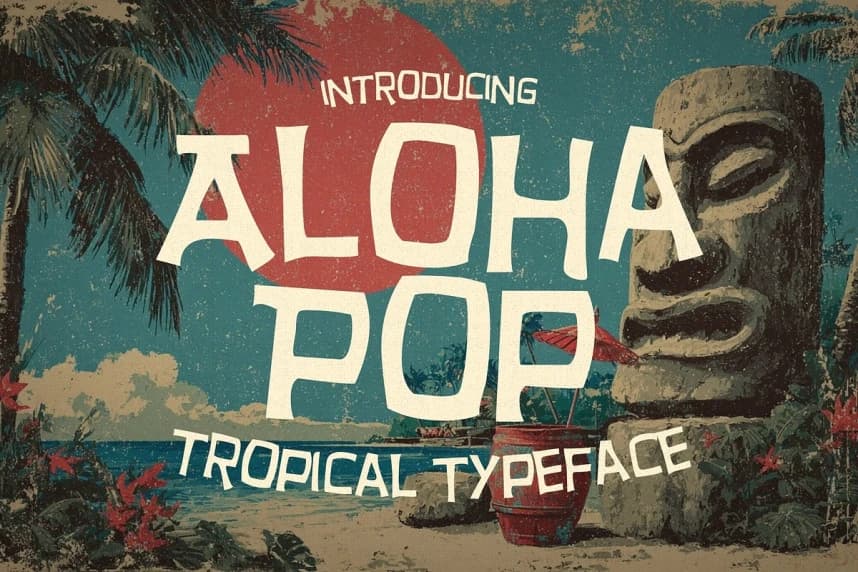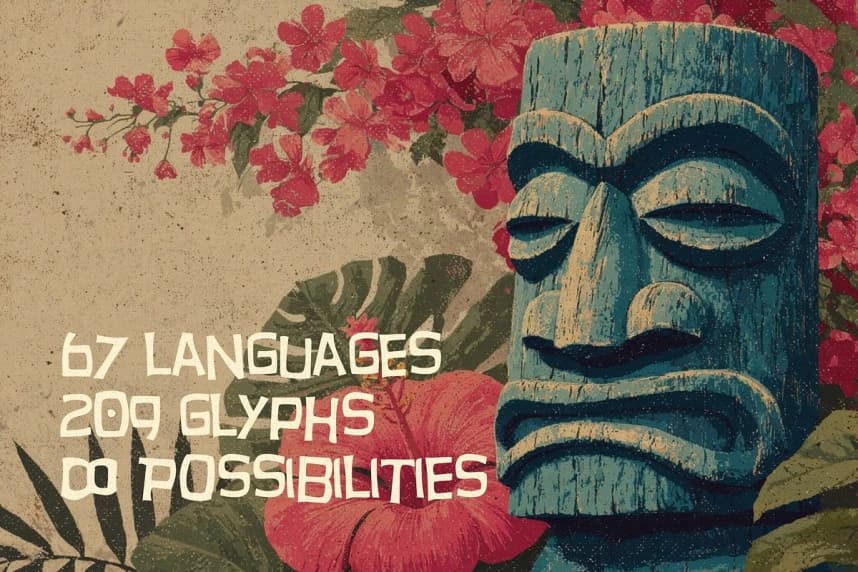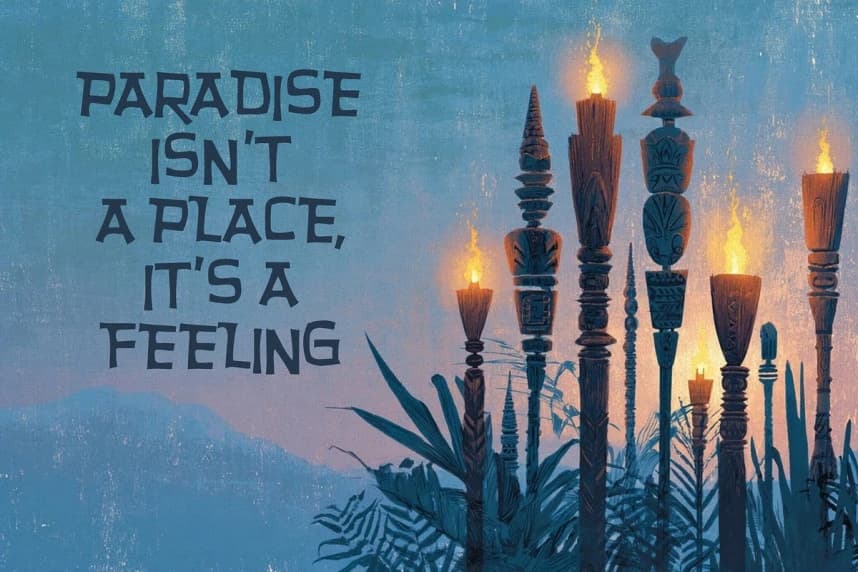
Aloha Pop Font
Aloha Pop Font, tropiklerin ruhunu her eğri ve çizgide yansıtan son derece el yapımı bir tipografidir. Eski tiki estetiğinden, Hawaii'nin cazibesi ve yazın kaygısız enerjisinden ilham alan bu cesur ve eğlenceli font, cennete giden pasaportunuzdur.
Aloha Pop Font, tropiklerin ruhunu her kıvrım ve çizgide yansıtan en üst düzey el yapımı tipografidir. Eski tiki estetiğinden, Hawaii cazibesinden ve yazın kaygısız enerjisinden ilham alan bu cesur ve neşeli font, cennete açılan pasaportunuzdur.